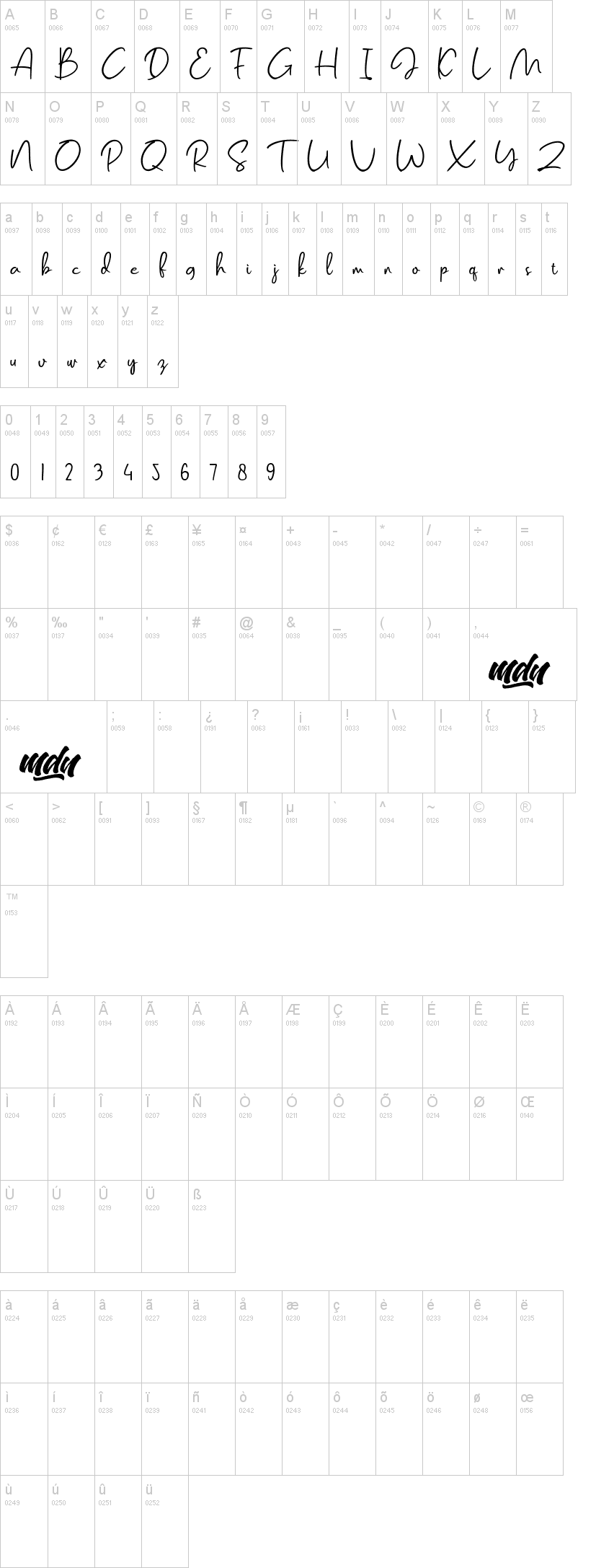
Salmon Script
Salmon Script 是一款手写字体,它的特点是具有温暖的色调,流畅的笔画,有助于提升文档的可读性。它的字体风格温柔可爱,有着柔和的曲线,可以轻松创造出温馨的设计效果。它适用于个人博客,节日祝福,书籍封面,海报,婚礼邀请等等。
Salmon Script是一款非常不错的手写艺术字体,具有很好的视觉感,适合于文化类的宣传设计、商业类品牌的广告和产品包装设计以及个性化文字排版等较多场景。
Salmon Script字符映射图